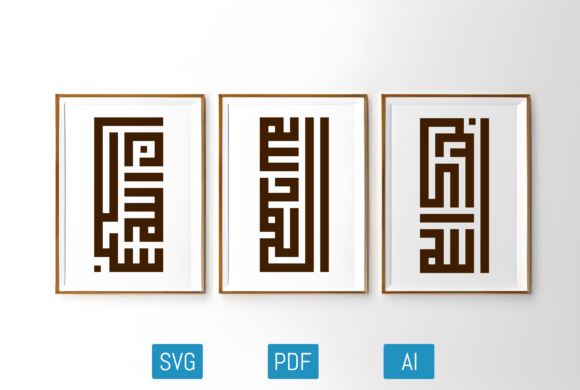
Modern Calligraphy Islamic Kufi 3 Vector
การค้นหาองค์ประกอบการออกแบบที่เหมาะสมอาจเป็นเรื่องท้าทาย แต่ Modern Calligraphy Islamic Kufi 3 Vector นำเสนอคอลเลกชันที่โดดเด่นซึ่งช่วยยกระดับงานของคุณได้ทันที